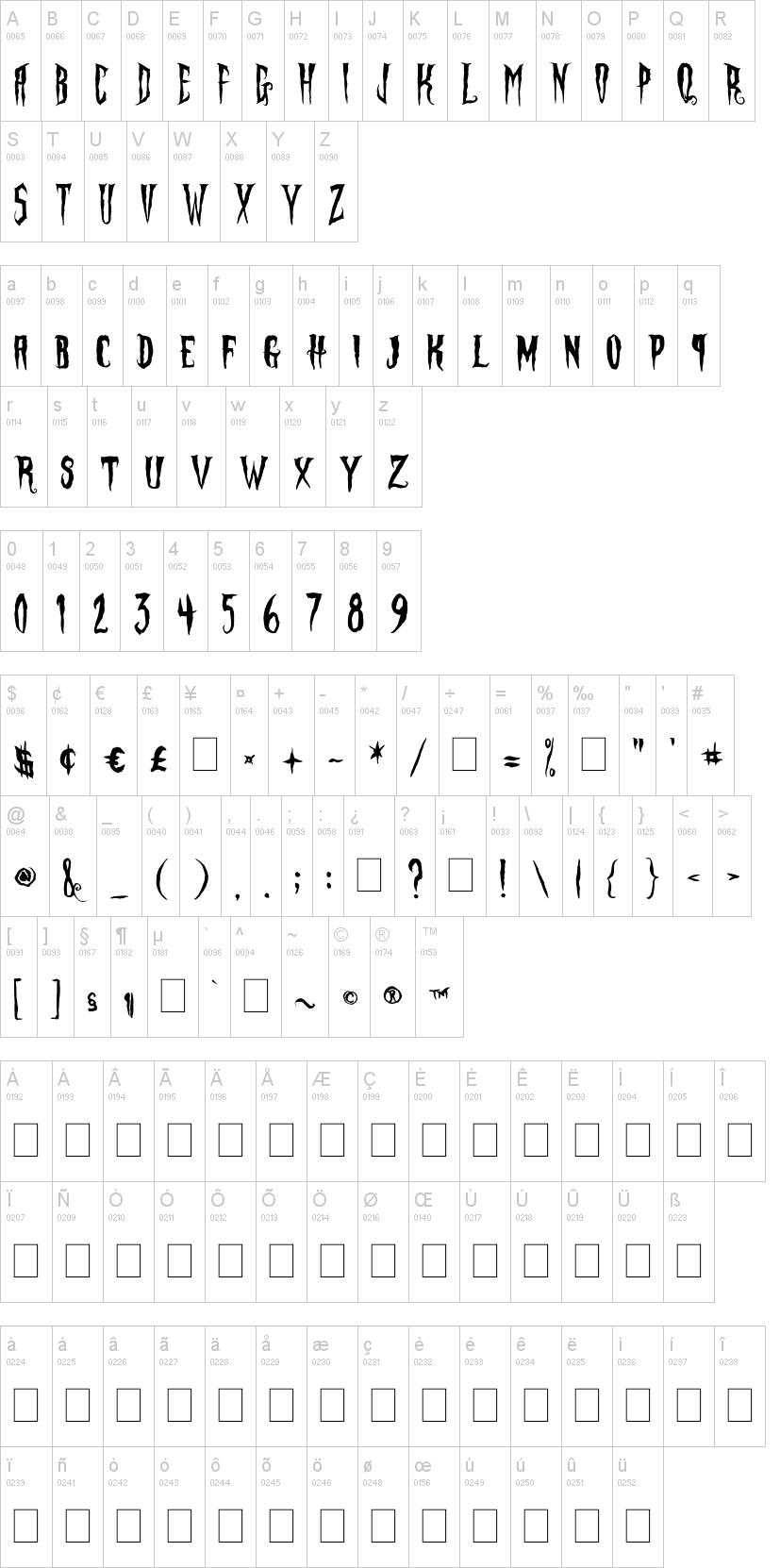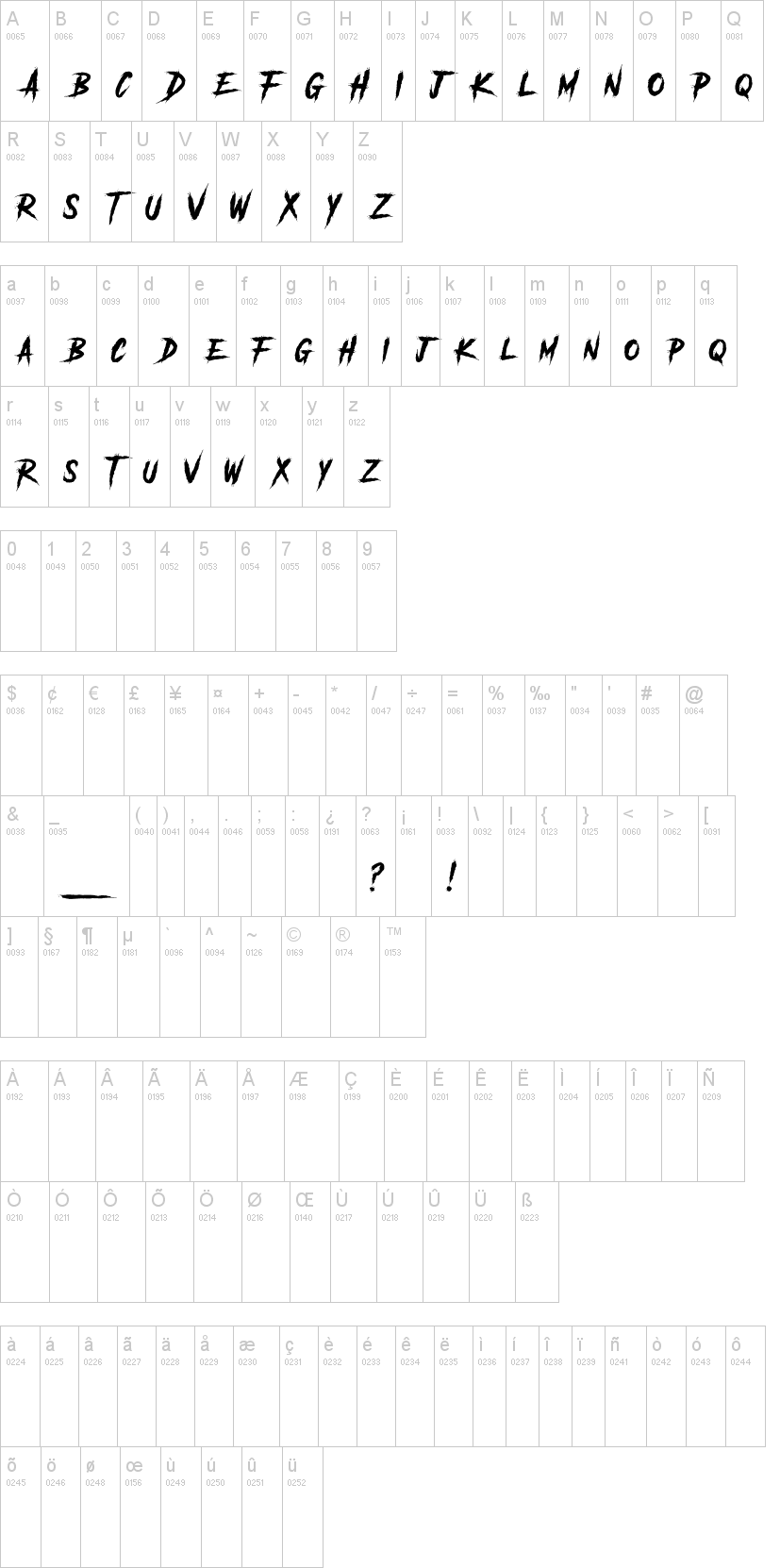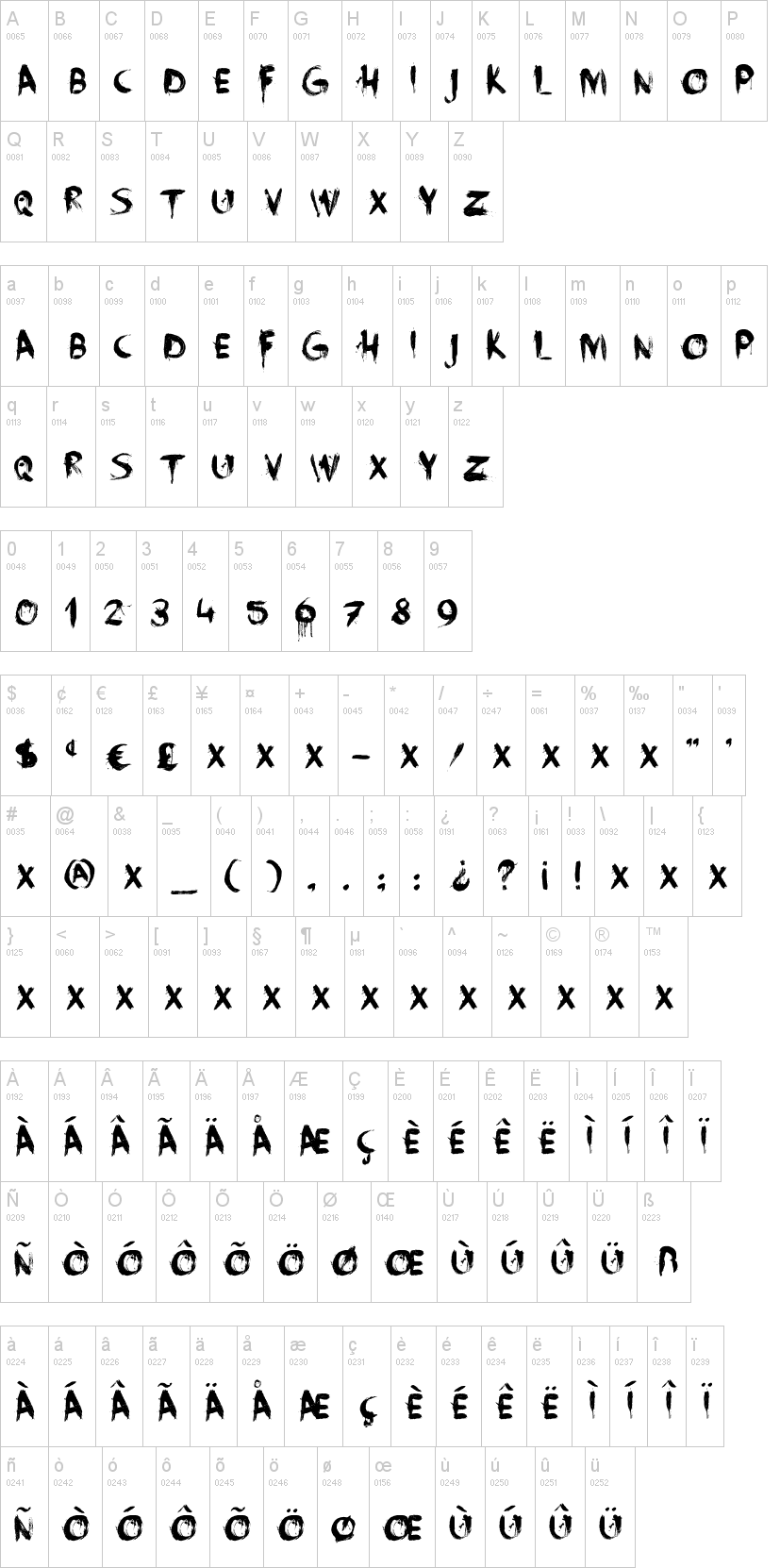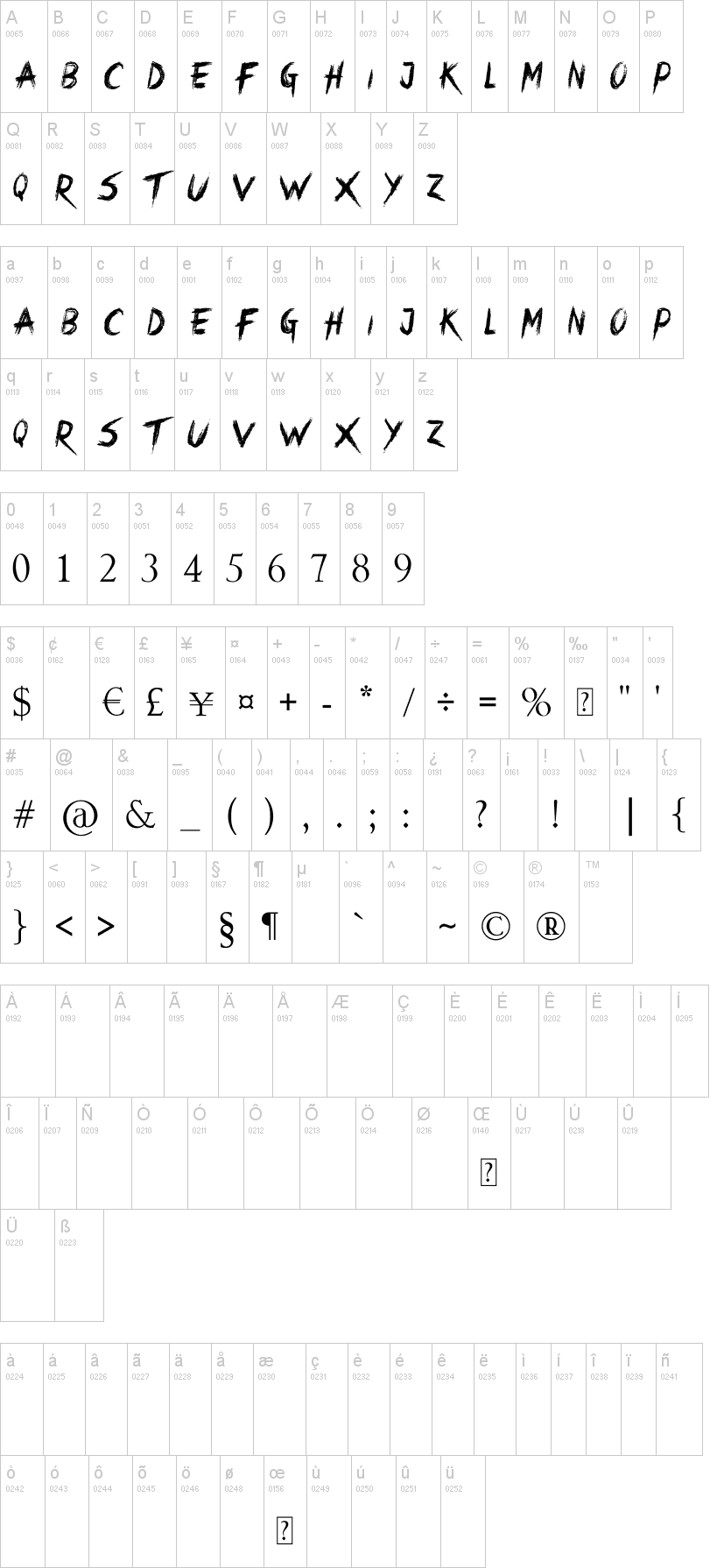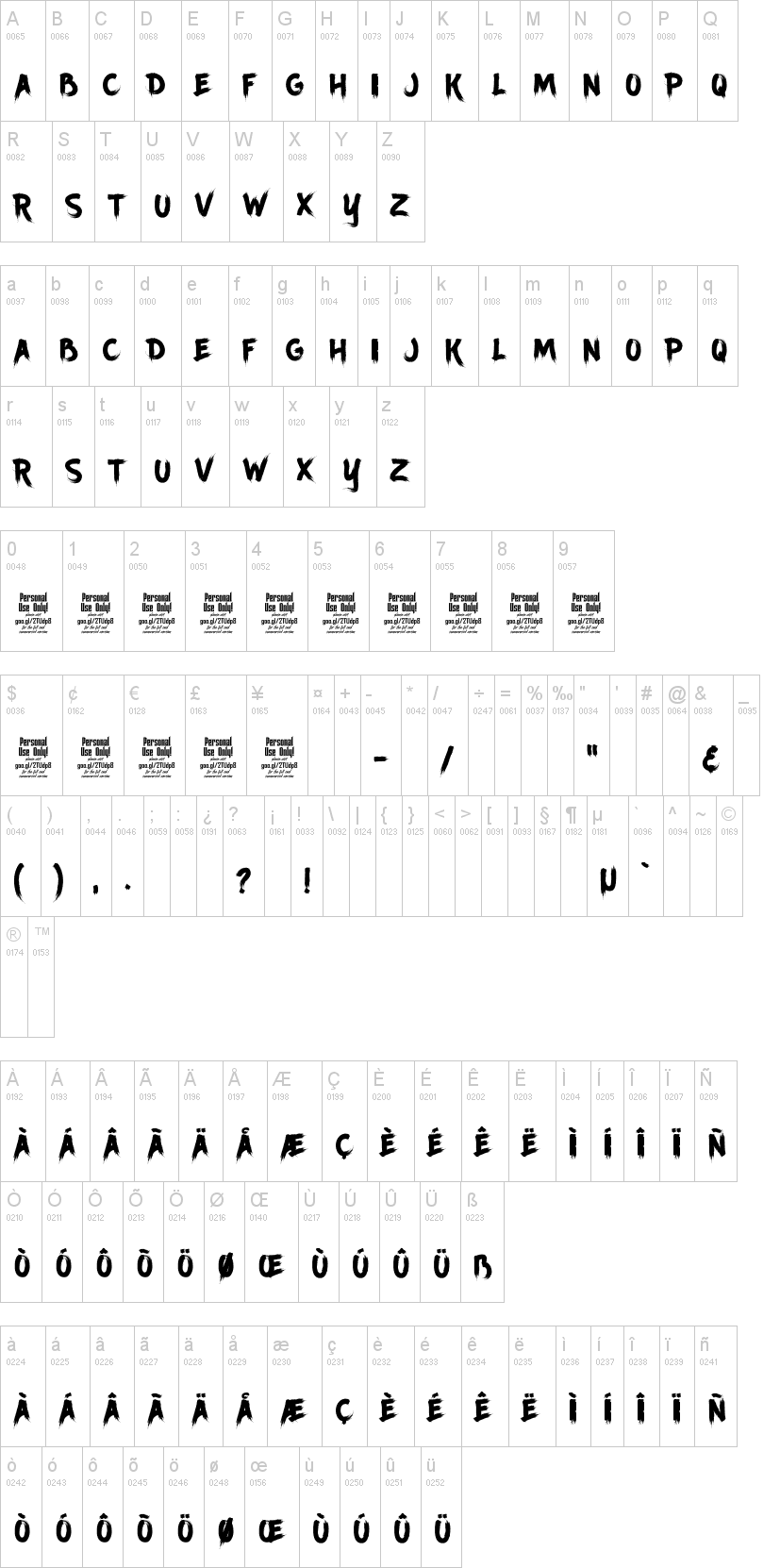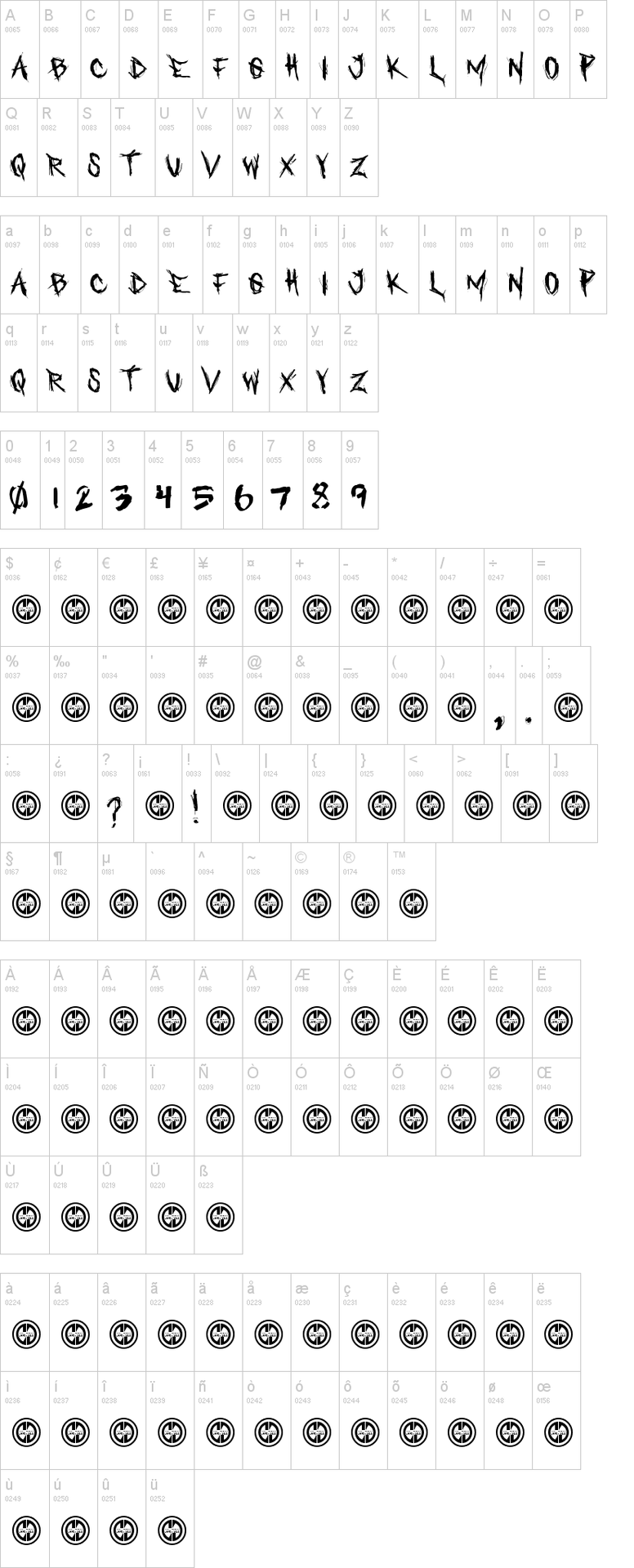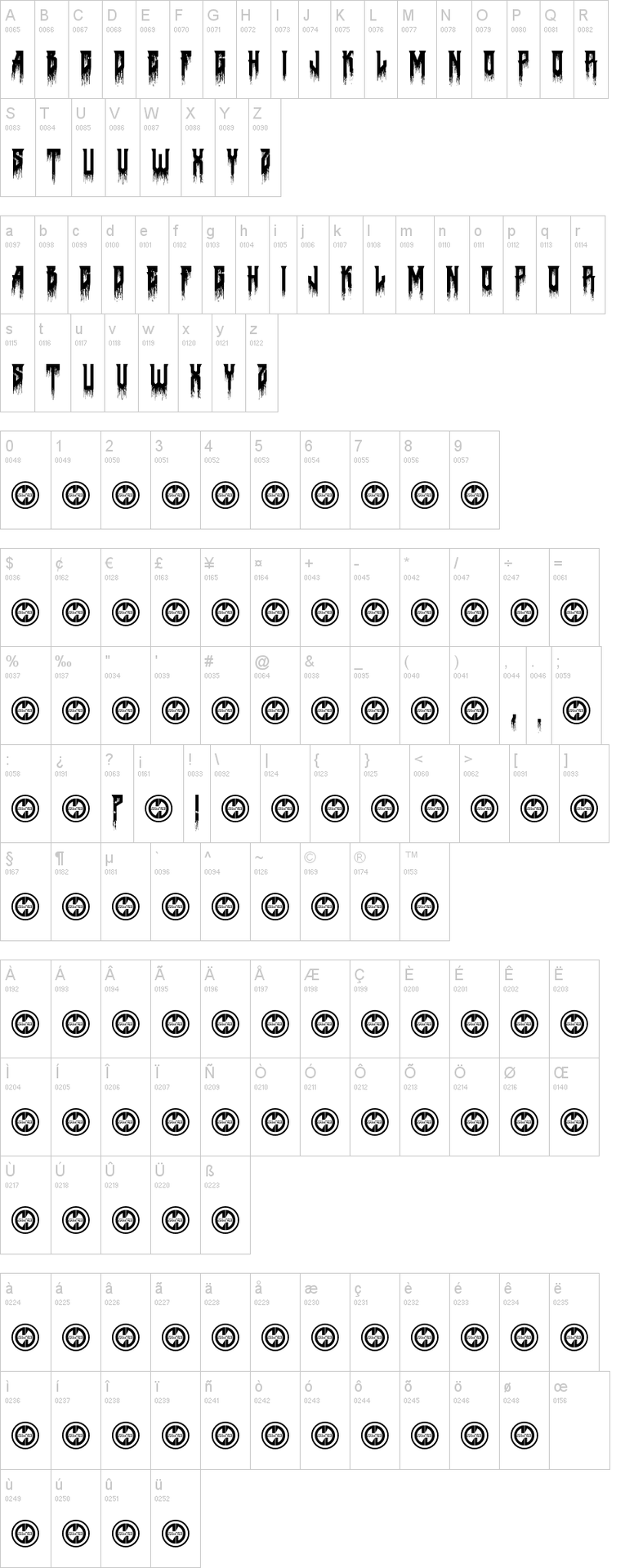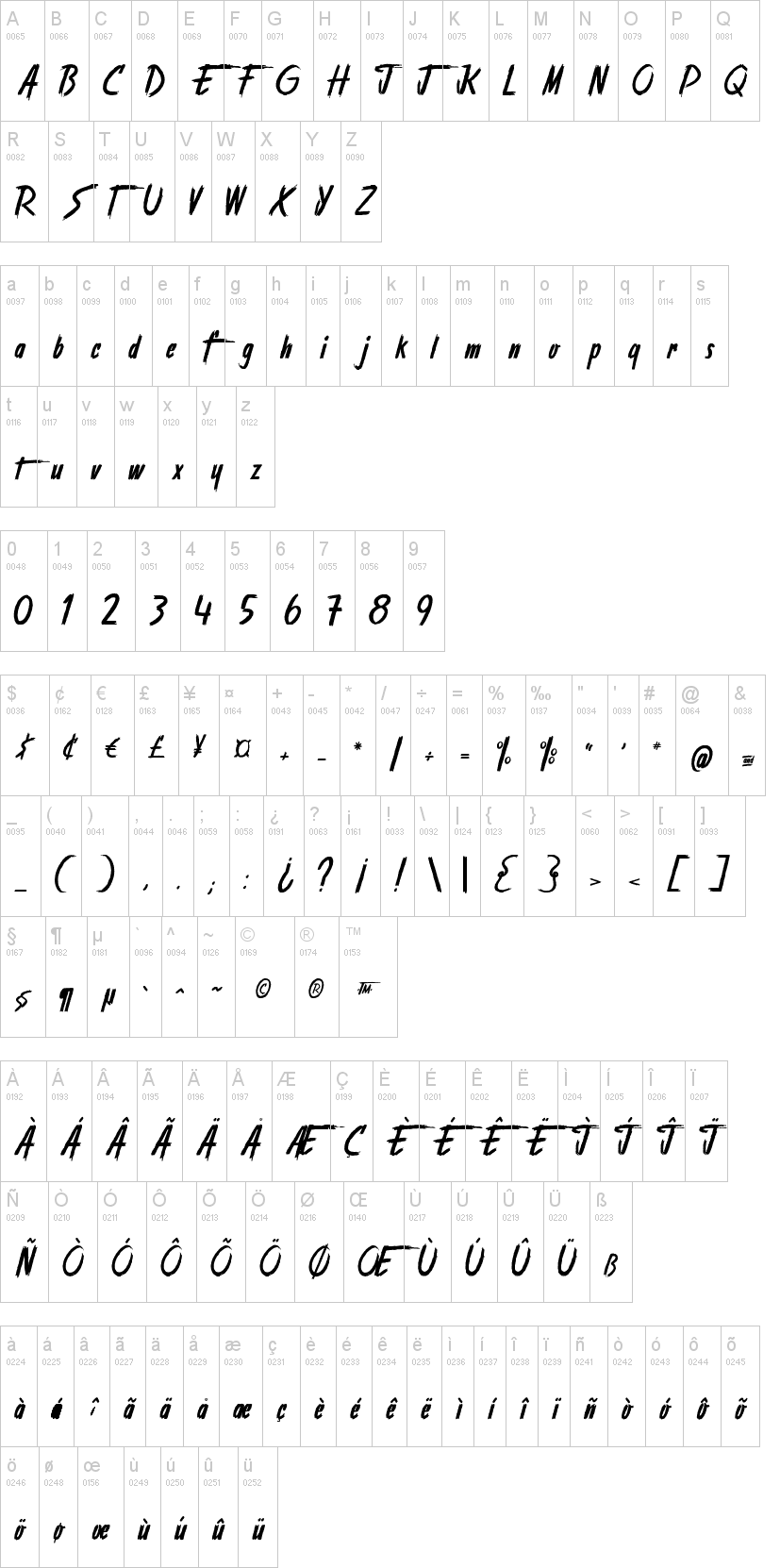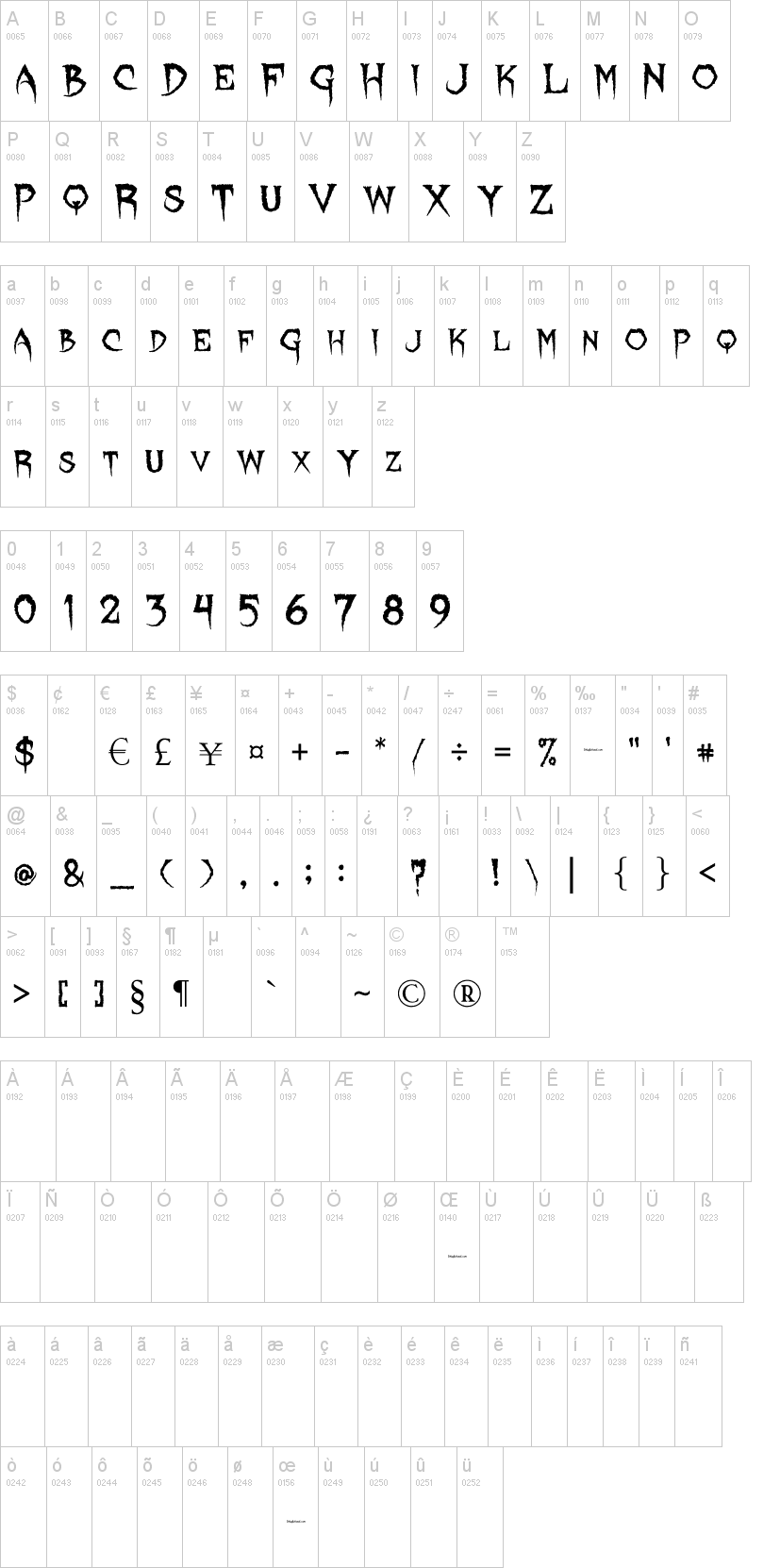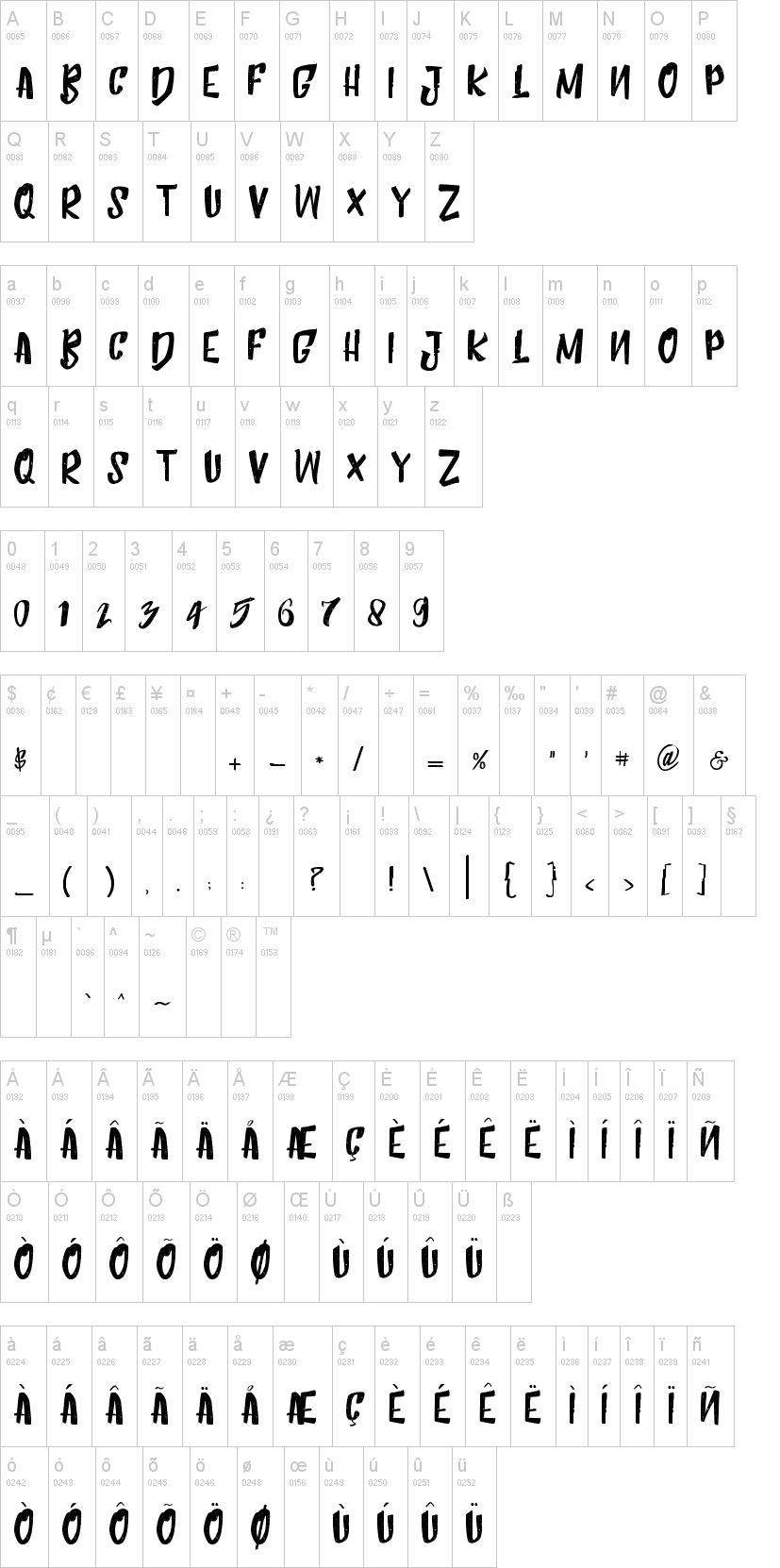
/HORROR FONTS/
> Như cái title rồi , mấy font này dùng theo horror style là hết bài. Có vài font tớ đã dùng rồi , như : Another Danger , True Lies . <
1/Another Danger
2/ True Lies
3/ Who asks Satan
4/Stranger back in the Night
5/ Friday 13th
4/ Death to Metal
5/Curse of the Zombie
6/Face your fears
7/Ancherr
8/Nightmare 5
9/ Horroroid
10/ Crimmes Times Six
11/ October Crow
12/ BangLYCH- Revenge Horror
13/ Bleeding Freaks
14/ Phantom Fingers
15/ Lycanthrope
16/ Humble Rought
17/ Sign Handwriting